Как определить шрифт по фотографии вывески или упаковки
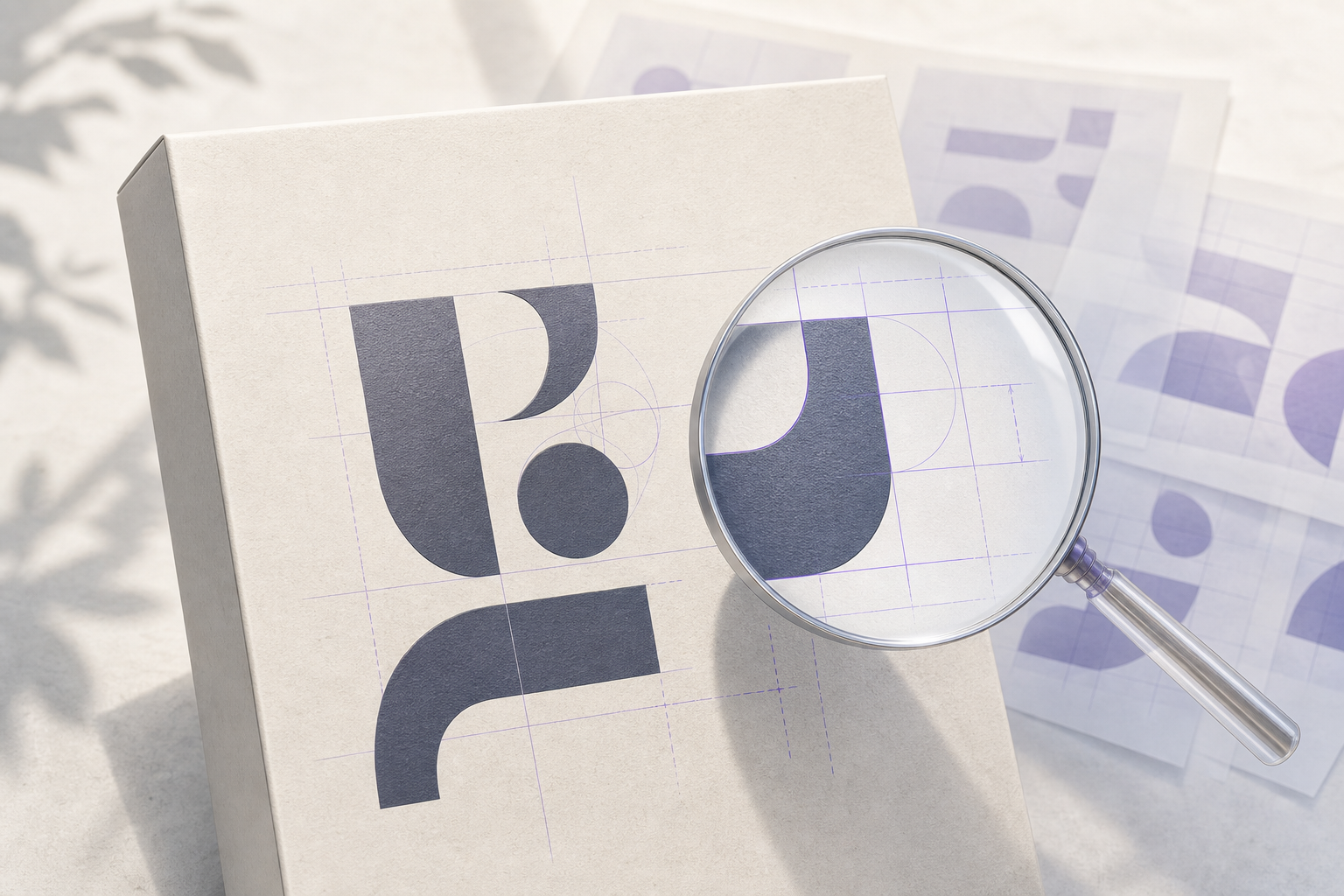
Определить шрифт по фотографии можно, если сначала улучшить снимок, выделить несколько характерных букв, затем сравнить их с образцами гарнитур и проверить результат вручную. Лучше всего распознаются фотографии с прямым ракурсом, хорошим контрастом и несколькими повторяющимися символами. Ниже — последовательный алгоритм для вывесок, этикеток и упаковки.
Почему распознавание шрифта по фото не всегда точно
Фотография показывает не сам шрифт, а его искажённое изображение. Перспектива, наклон поверхности, блики, тени, низкое разрешение, сжатие и декоративная обработка меняют пропорции букв. Кроме того, на упаковке часто используется не готовая гарнитура, а изменённый логотип: дизайнер мог вручную исправить отдельные знаки, соединить буквы или нарисовать слово заново.
Поэтому корректная цель — не всегда найти точное название файла шрифта. Иногда достаточно определить класс гарнитуры и подобрать близкий вариант с похожими шириной, контрастом, толщиной и характером деталей. Для восстановления логотипа потребуется дополнительная отрисовка, а для обычного текста на ценнике или вывеске обычно удаётся найти исходный или очень близкий шрифт.
Подготовьте фотографию перед поиском шрифта
Качество исходного изображения напрямую влияет на результат. Перед распознаванием обрежьте фотографию так, чтобы в кадре остался текст и небольшой запас вокруг него. Уберите лишний фон, выровняйте горизонт, исправьте перспективу и увеличьте область с буквами. Если надпись снята под углом, сначала приблизительно восстановите прямоугольную форму строки.
Полезно подготовить несколько версий одного снимка: цветную, чёрно-белую, с повышенным контрастом и с мягким увеличением резкости. Слишком сильная резкость создаёт ложные выступы на контурах, поэтому обработка не должна дорисовывать детали. Не используйте маленький скриншот из мессенджера, если есть возможность получить оригинальную фотографию.
- Выберите самый резкий кадр с минимальным количеством бликов.
- Обрежьте изображение до одной надписи или отдельного слова.
- Выровняйте перспективу и попробуйте убрать наклон строки.
- Отделите буквы от фона с помощью контраста или чёрно-белого режима.
- Сохраните исходник, чтобы сравнивать результат с необработанной фотографией.
Пошаговый алгоритм идентификации гарнитуры
Надёжнее двигаться от общего к частному: сначала определить тип шрифта, затем изучить отдельные знаки и только после этого искать название. Такой подход снижает количество случайных совпадений. Один похожий символ ещё не доказывает совпадение, а несколько одинаковых особенностей в разных буквах уже позволяют сузить круг вариантов.
Шаг 1. Найдите самые информативные буквы
Выберите буквы, форма которых хорошо различается у разных гарнитур. В латинице это часто G, R, Q, a, g и e, а в кириллице — Д, Ж, К, Л, У, Ф, я и строчные а, б, д. Обратите внимание на хвосты, перекладины, верхние элементы, форму овалов и соединение штрихов. Чем больше разных знаков в образце, тем полезнее сравнение.
Шаг 2. Определите класс и настроение шрифта
Сначала решите, к какой группе относится надпись: антиква с засечками, гротеск без засечек, рукописный, моноширинный, декоративный или акцидентный шрифт. Затем оцените настроение: строгий, технический, гуманистический, геометрический, винтажный или нейтральный. Класс не даёт точного названия, но отсекает неподходящие варианты и помогает искать не по одному слову, а по визуальному контексту.
Шаг 3. Сравните пропорции и насыщенность
Сопоставьте ширину букв, высоту строчных знаков, толщину основных и соединительных штрихов, размер внутренних просветов и расстояние между символами. Две гарнитуры могут иметь одинаковые засечки, но заметно отличаться по ширине и плотности. Для вывески особенно важны общий ритм строки и силуэт слова, а для упаковки — контраст, компактность и поведение текста в небольшом размере.
Шаг 4. Проверьте несколько слов, а не одну букву
Наберите текст с фотографии в предполагаемых шрифтах и сравните его рядом с оригиналом. Смотрите не только на отдельные буквы, но и на слово целиком: совпадают ли наклон, ширина, высота, интервалы и характер окончания штрихов. Если один знак выглядит иначе, это может быть особенностью конкретного начертания, ошибкой фотографии или ручной модификацией логотипа.
Шаг 5. Уточните начертание и лицензию
Даже найденная гарнитура может не совпасть по весу и ширине. Проверьте варианты Regular, Medium, Semibold, Bold, Condensed и Extended, если они доступны. Для коммерческого использования отдельно выясните условия лицензии: право на личные проекты не всегда разрешает рекламу, упаковку, наружную вывеску или передачу изменённого файла заказчику.
Как распознать шрифт без автоматического сервиса
Автоматический распознаватель полезен как отправная точка, но не заменяет визуальную проверку. Если сервис не даёт результата, увеличьте изображение и составьте собственное описание: есть ли засечки, как устроена буква а, открыта ли буква е, наклонена ли ось овалов, имеет ли R диагональную ножку и насколько широки заглавные. Затем ищите гарнитуры по сочетанию этих признаков в каталогах шрифтов.